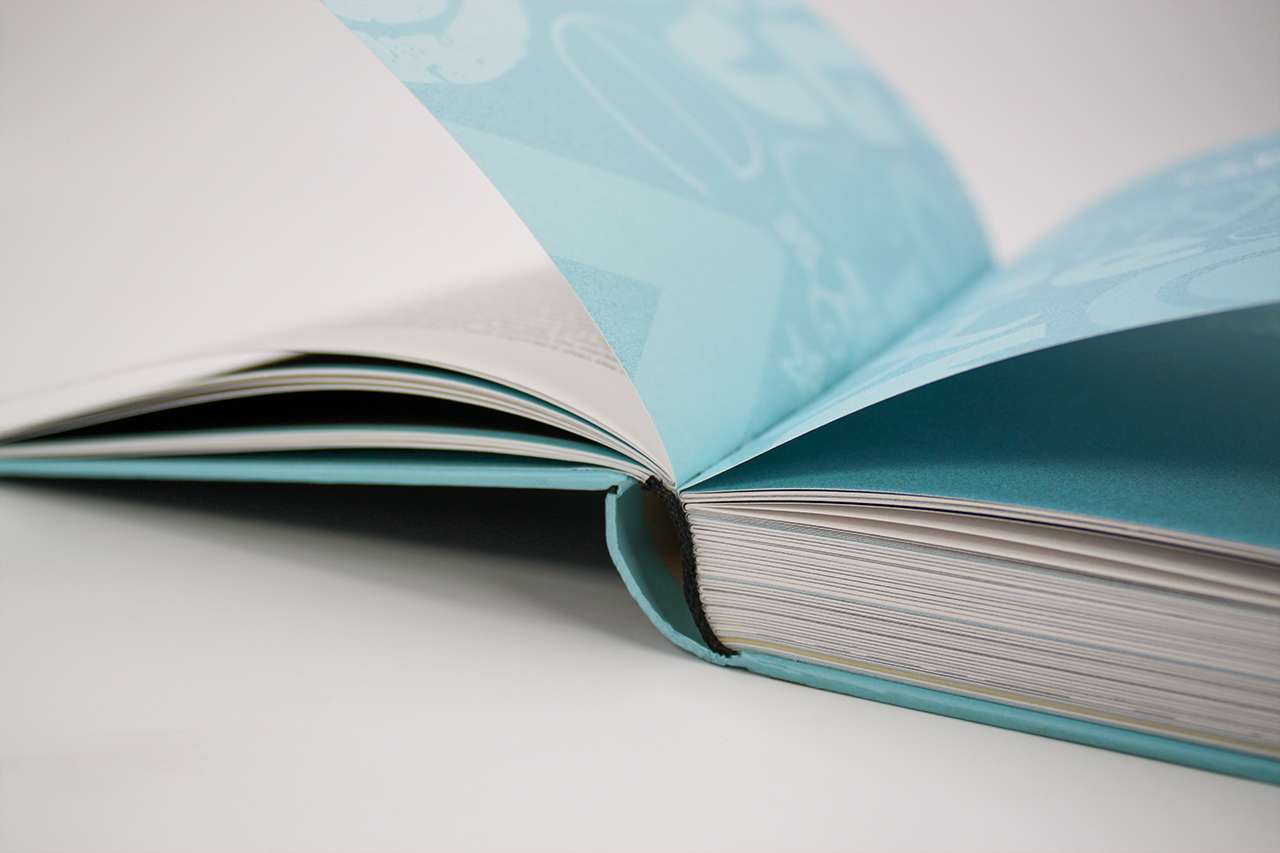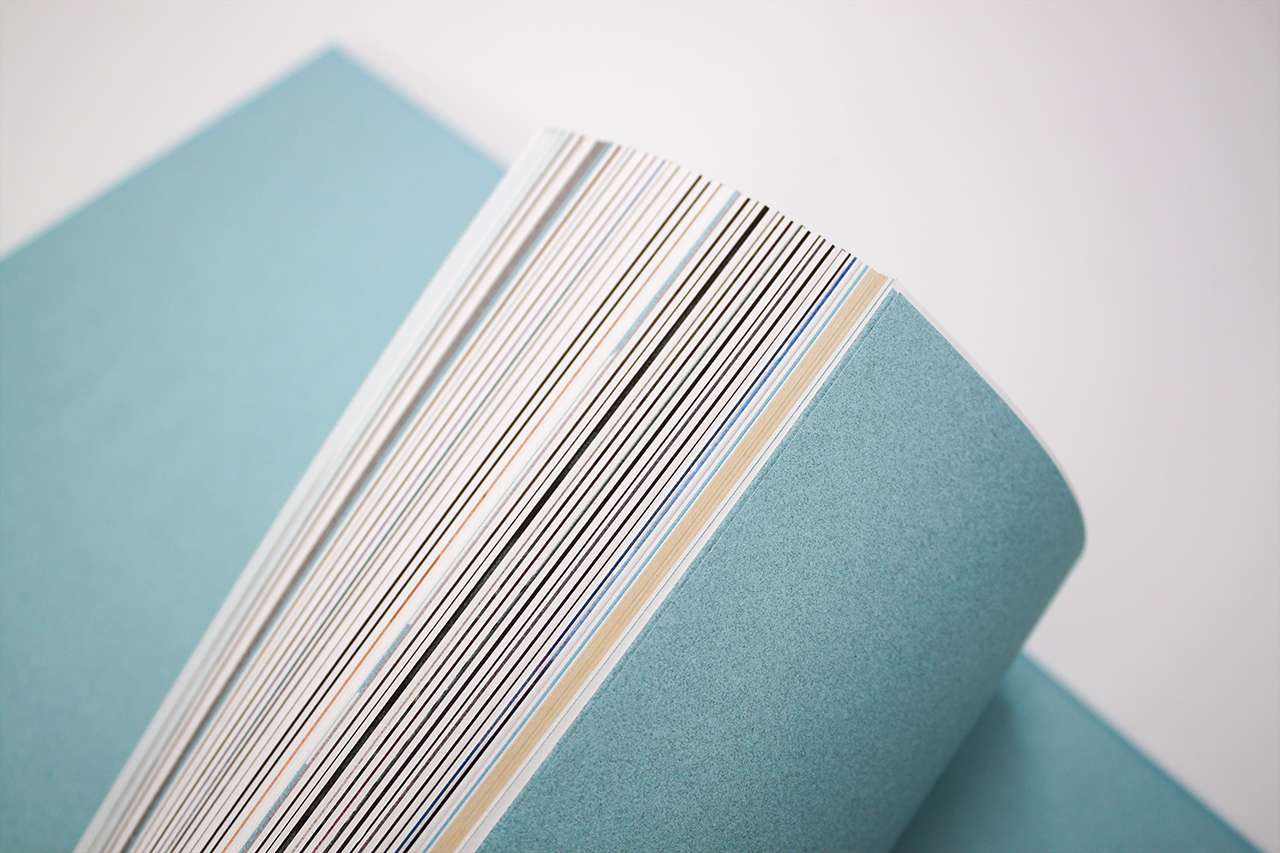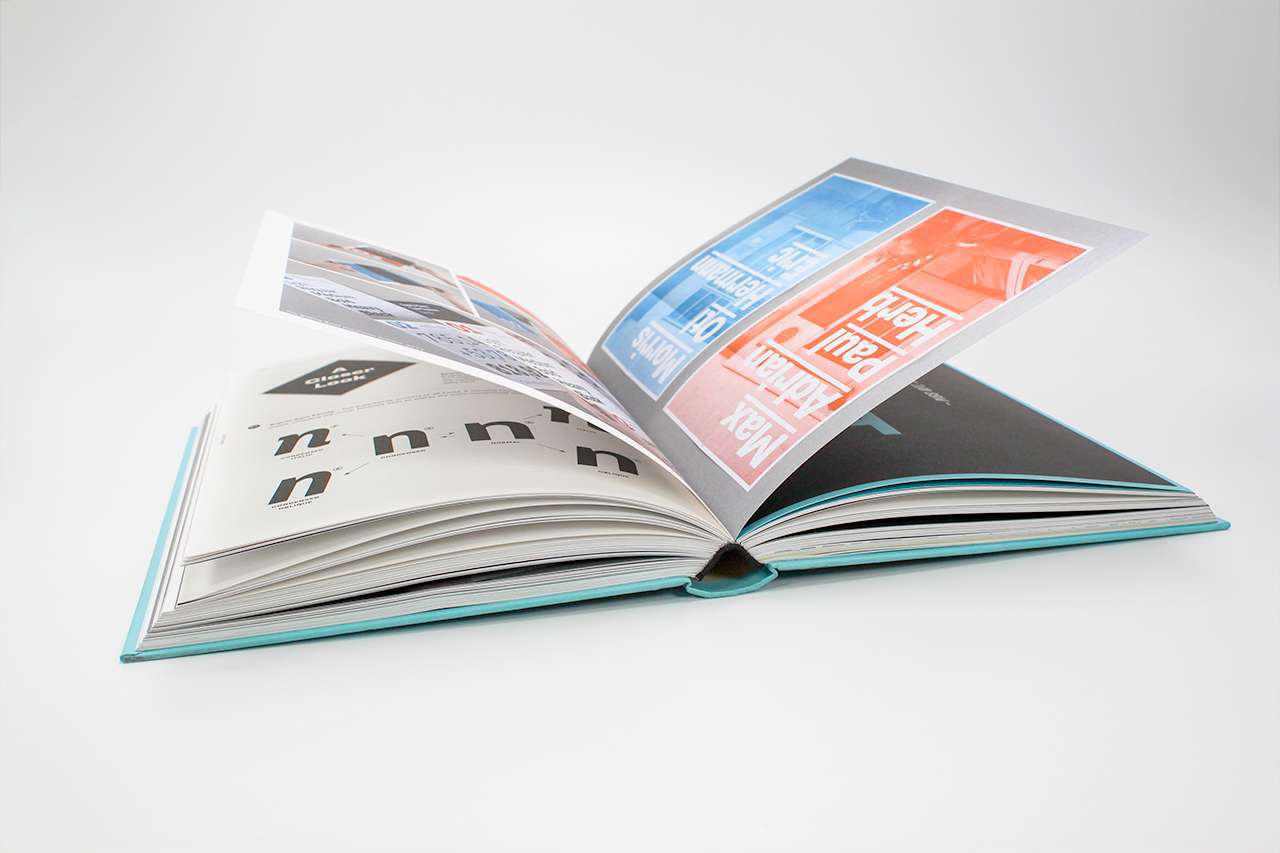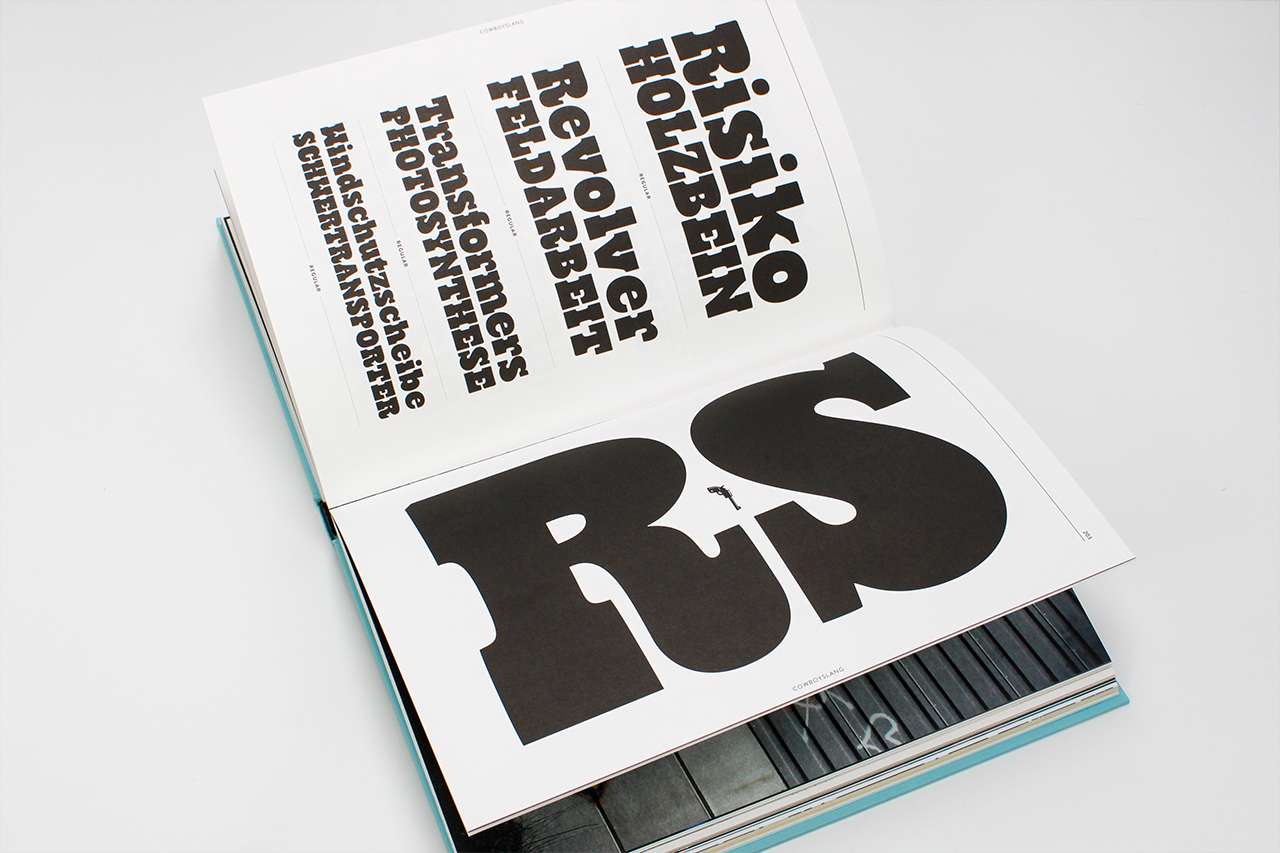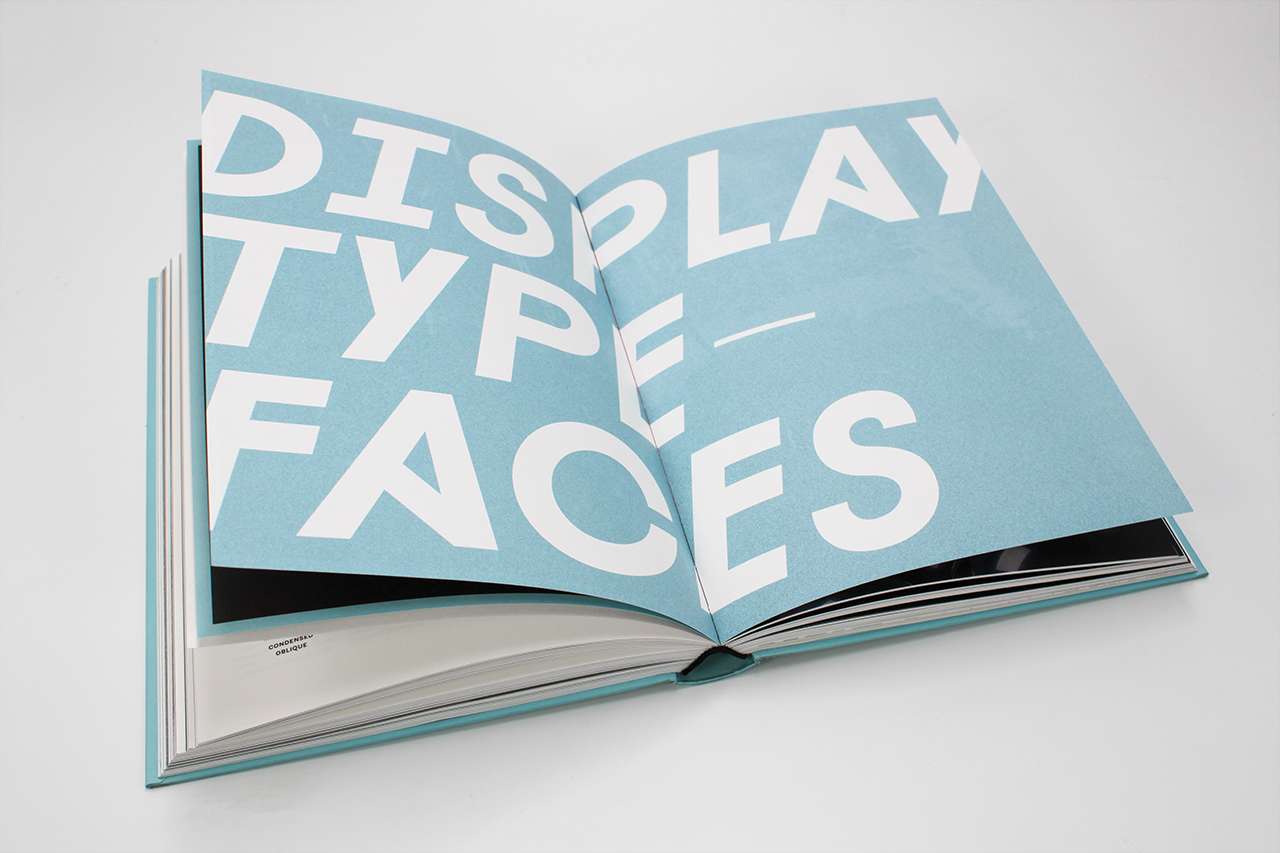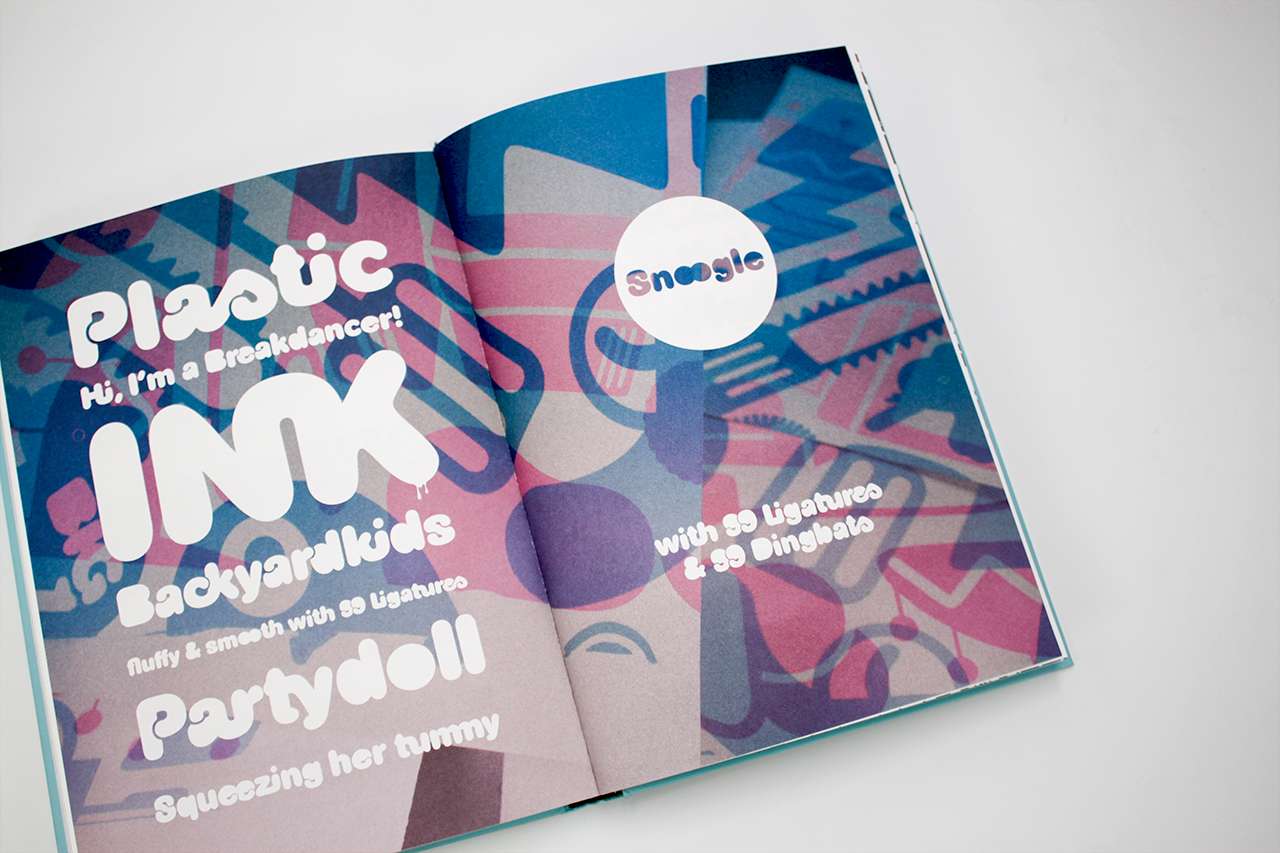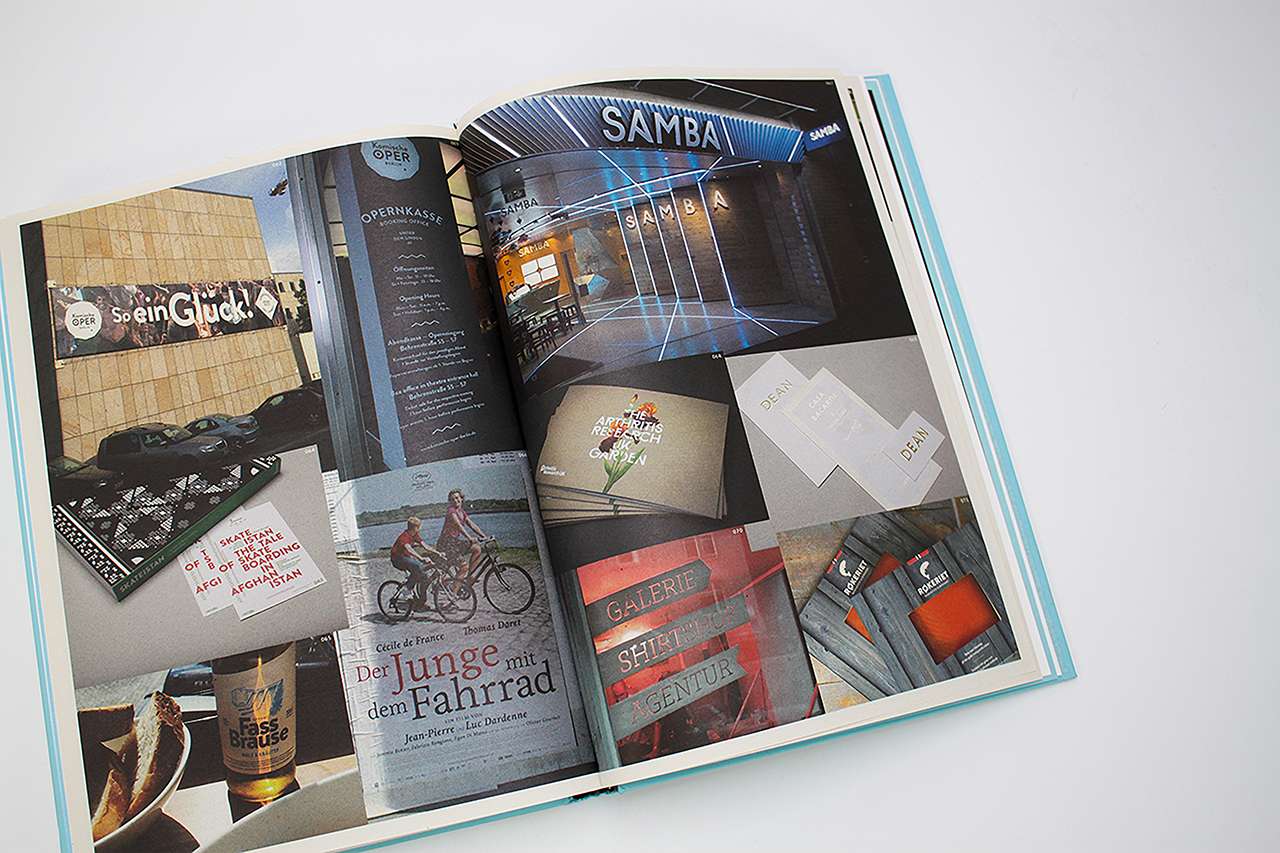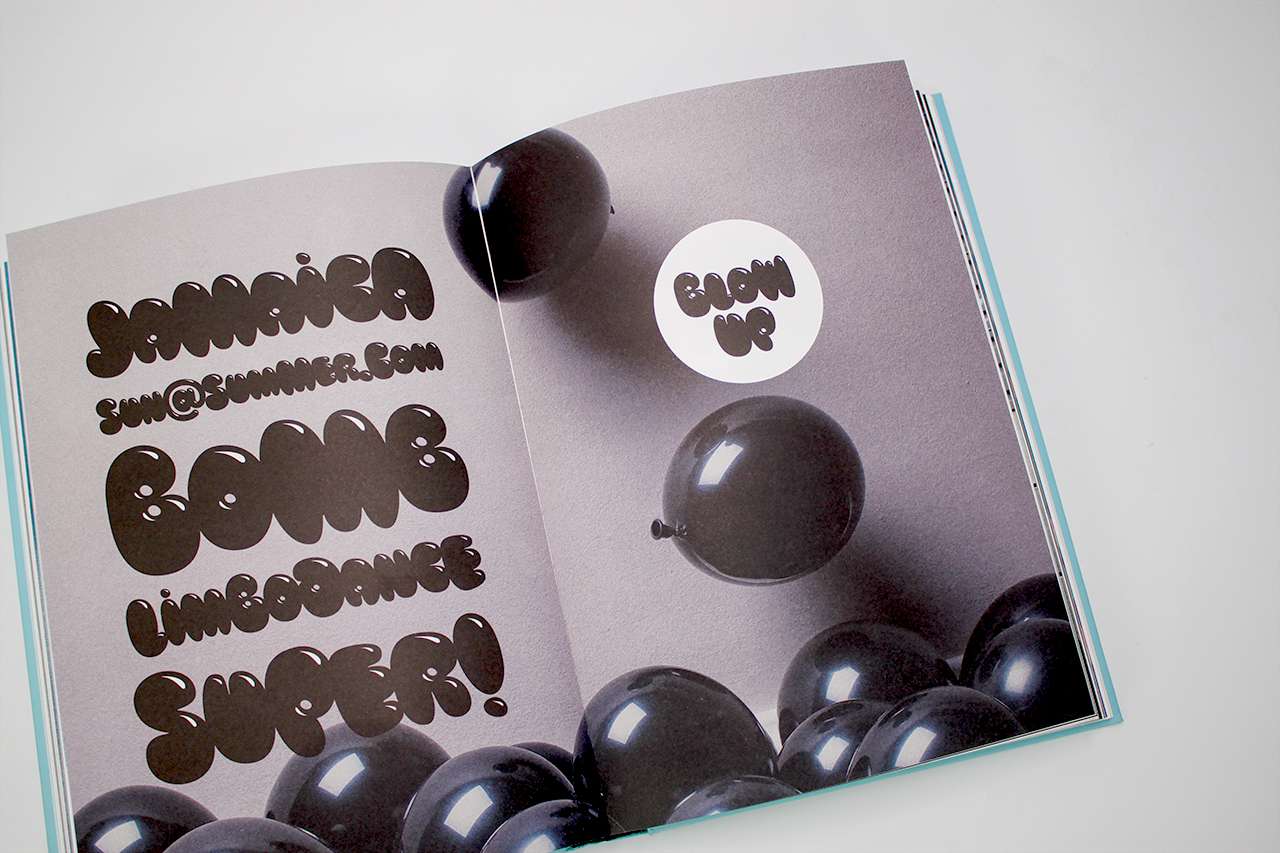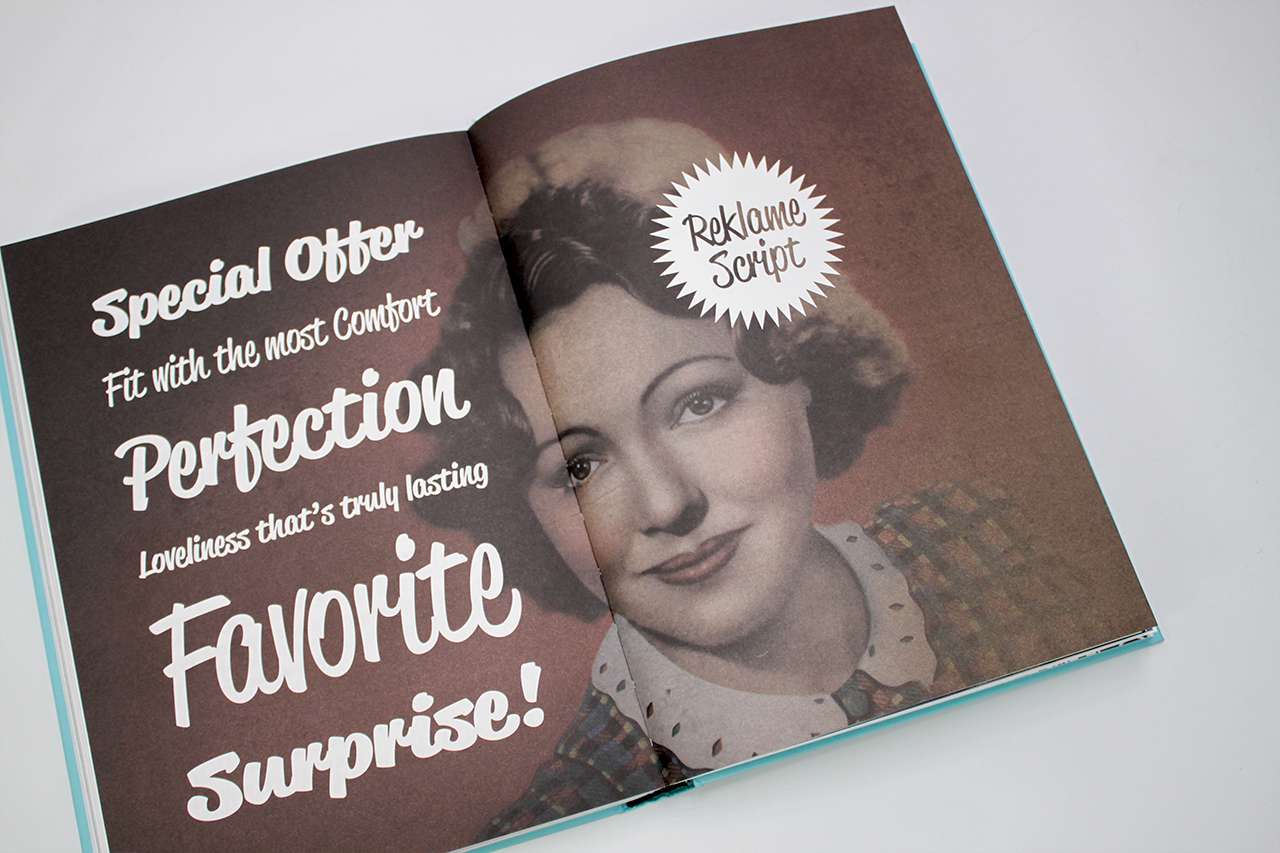
Lernen von den Besten
Hannes von Döhren hat geschafft, wovon tausende Typedesigner:innen träumen: Er lebt von seinen Schriften. Mit HVD-Fonts hat er seinen eigenen Schriftvertrieb, mit der Brandon einen Welt-Bestseller. Sein Erfolgsprinzip und seine vielfach ausgezeichneten Schriften präsentiert er in diesem Buch.
»On the streets you look at girls – I look at type.« Und im Supermarkt spielt er Grill vs. Dax und kauft sein Essen nach lettering. Vor sechs Jahren beschloss er, jeden Tag mindestens einen Buchstaben zu zeichnen und davon zu leben. Beobachten, Begeisterung und Beharrlichkeit führten zum TDC-Award und zum Durchbruch.
In diesem Buch stellt er nicht nur seine Brotschriften, Displayfonts und Schriftfamilien vor, sondern verrät auch seine Erfolgsgeheimnisse: von Kooperation statt Konkurrenz über Vertrieb und Social Media bis zum Umgang mit Sprayerschriften. Mit Beiträgen von Erik Spiekermann, Jan Middendorp und Livius Dietzel und fünf Fonts im Wert von 99 US-Dollar zum freien Download.
Hannes von Döhren: »Eine moderne Schriftenfamilie sollte eine Seele haben, ein Gefühl vermitteln, die Betrachtenden berühren und eine Daseinsberechtigung haben. Und sie sollte die technischen Anforderungen erfüllen, wie gutes Spacing und Kerning, saubere Kurven, Sprachausbau, OpenType-Features, gute Bildschirmdarstellung … «
Every Day I Draw at Least One Letter
The HvD Fonts Type Book